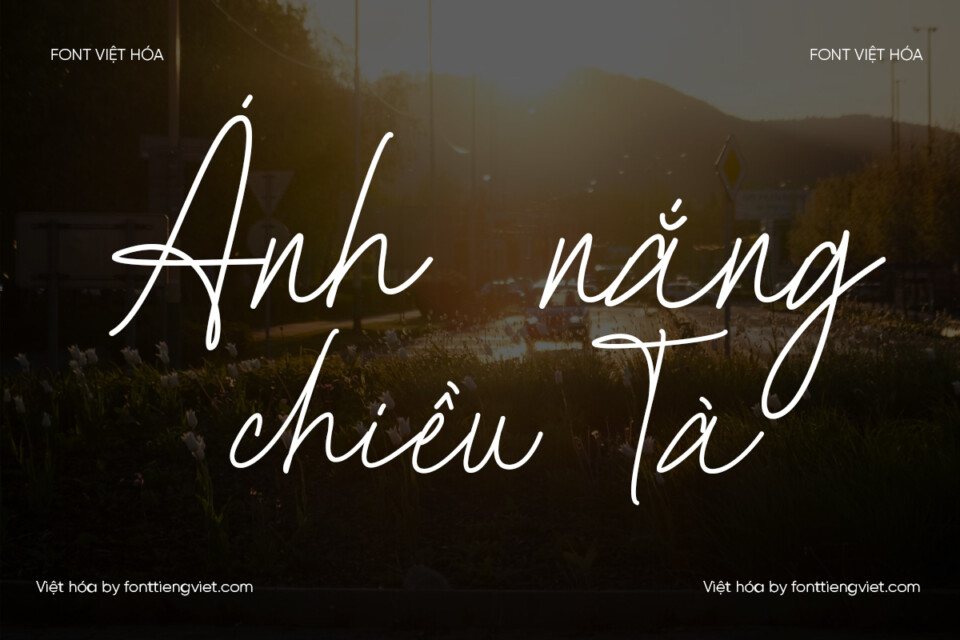
Giới thiệu về Font Việt hóa 1FTV VIP Celestial Dream
Trong thế giới đồ họa hiện đại, việc tìm kiếm một bộ Font Chữ đáp ứng cả tính thẩm mỹ lẫn sự tiện dụng luôn là ưu tiên hàng đầu. Font Việt hóa 1FTV VIP Celestial Dream nổi lên như một lựa chọn hoàn hảo cho những ai yêu thích phong cách tinh tế và huyền ảo. Đây là bộ phông chữ mang đậm nét nghệ thuật, lấy cảm hứng từ những giấc mơ và bầu trời sao lấp lánh, giúp các ấn phẩm thiết kế trở nên nổi bật và thu hút ánh nhìn hơn bao giờ hết.
Đặc điểm nổi bật của Celestial Dream
Bộ phông chữ này sở hữu các đường nét thanh mảnh nhưng không kém phần chắc chắn, tạo cảm giác bay bổng và sang trọng. Đặc biệt, phiên bản Font Việt hóa 1FTV VIP Celestial Dream đã được tối ưu hóa hoàn toàn hệ thống dấu tiếng Việt, giúp người dùng không còn lo lắng về lỗi hiển thị hay mất ký tự khi soạn thảo văn bản. Điều này cực kỳ hữu ích cho các bạn học sinh trong việc trình bày báo tường hoặc thầy cô thiết kế giáo án điện tử sinh động.
Ứng dụng thực tế của Font Việt hóa 1FTV VIP Celestial Dream
Với vẻ đẹp thiên hà đầy lôi cuốn, bộ chữ này thường được sử dụng trong các dự án thiết kế thiệp mời, bìa sách, poster sự kiện hoặc các tiêu đề trang web nghệ thuật. Sự kết hợp giữa nét chữ mềm mại và các ký tự đặc biệt giúp nâng tầm giá trị cho mọi sản phẩm truyền thông. Ngoài ra, tính tương thích cao trên các phần mềm như Photoshop hay Canva giúp người dùng dễ dàng thao tác và sáng tạo không giới hạn.
Lý do nên lựa chọn font chữ này
Không chỉ miễn phí cho mục đích cá nhân, phông chữ này còn mang lại sự chuyên nghiệp nhờ cách sắp xếp kerning chuẩn xác. Việc sử dụng Font Việt hóa 1FTV VIP Celestial Dream giúp tiết kiệm thời gian chỉnh sửa thủ công, mang lại hiệu quả công việc cao nhất.
Kết luận về bộ font chất lượng